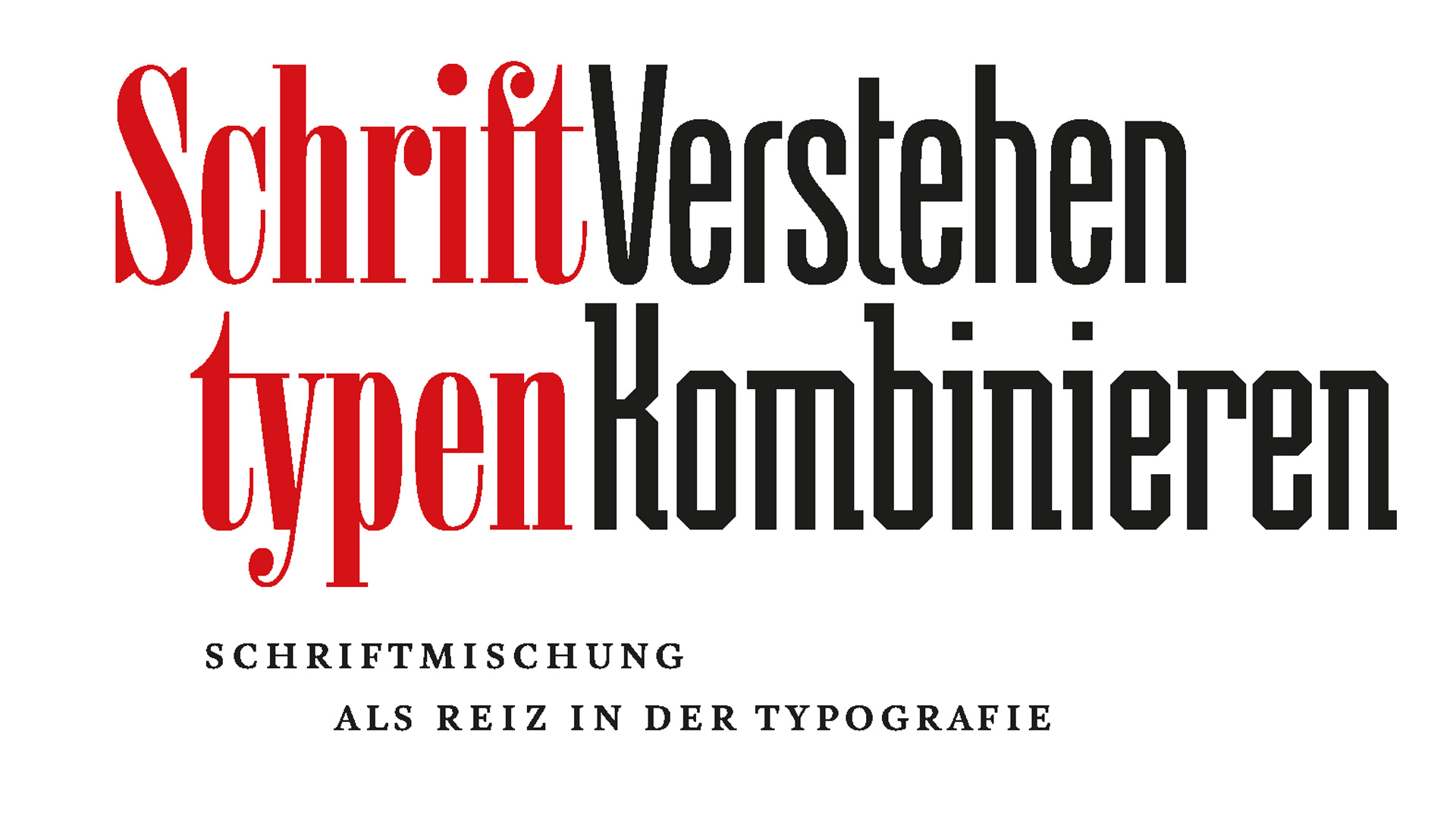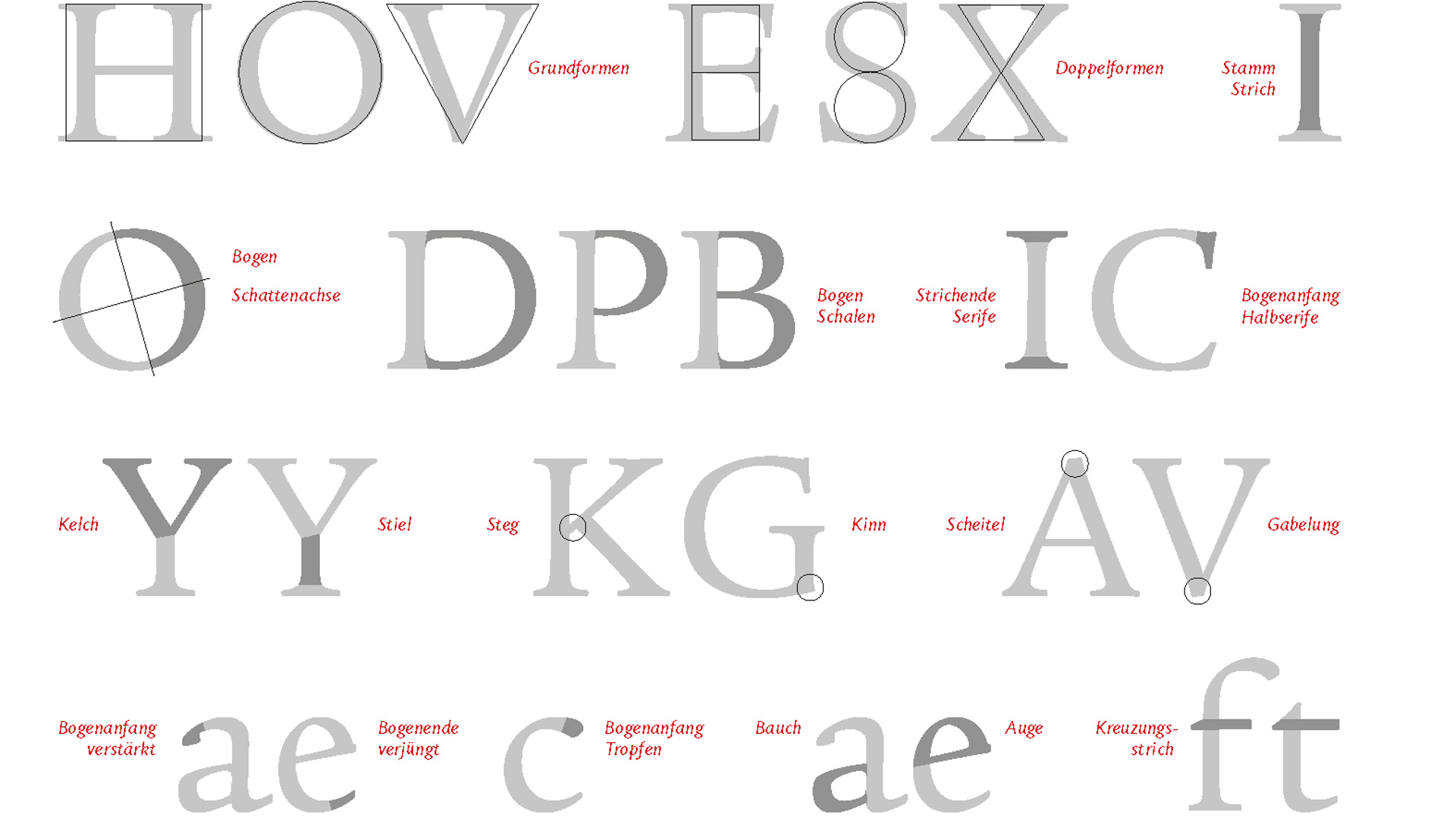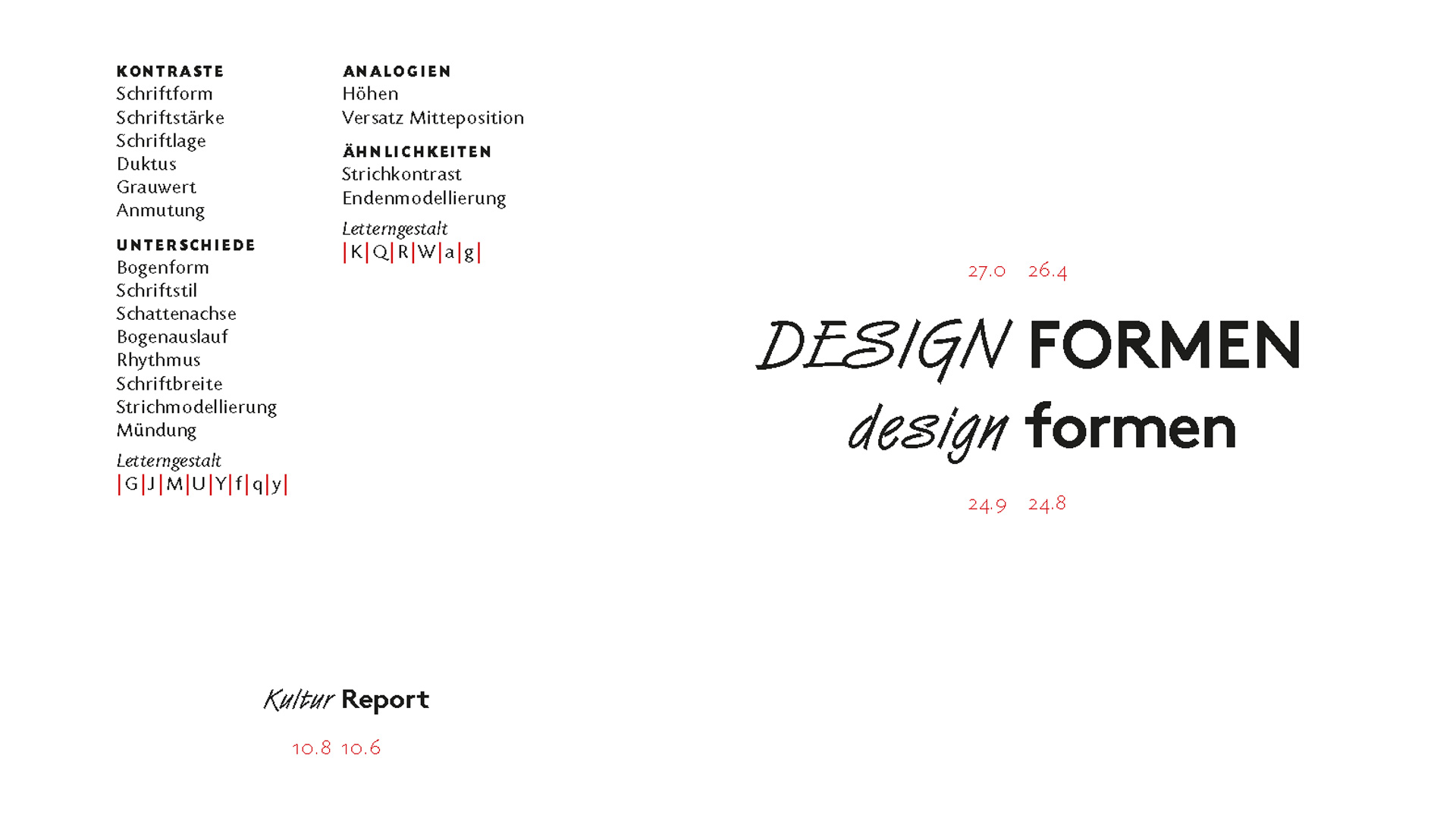
Philipp Stamm, Professor am Institut Visuelle Kommunikation, hat ein fantastisches Handbuch für alle Freund*innen der Schriftmischung beim Birkhäuser Verlag herausgebracht:
Unter dem Titel Schrifttypen – Verstehen / Kombinieren bringt er uns der Schriftmischung als eine der grossen Herausforderungen und gleichzeitig als ein steter Reiz in Typografie und Grafikdesign näher:
Soll sie opulent, nur eingeschränkt oder am besten gar nicht stattfinden? Durch das detaillierte Betrachten der Schriftgestalt und eine erneuerte Schriftklassifikation, eröffnet Prof. Philipp Stamm ein vertieftes Verständnis für die Vielfalt bestehender Schriftformen und gibt durch seine systematische Analyse von Analogie und Kontrast Einblick in die benötigten Kriterien für das Kombinieren von Schriften.
Im Frühjahr erscheint auch der englische Titel im Birkhäuser Verlag:
Understanding / Combining · Typefaces.
Typeface combination as typographic stimulus.